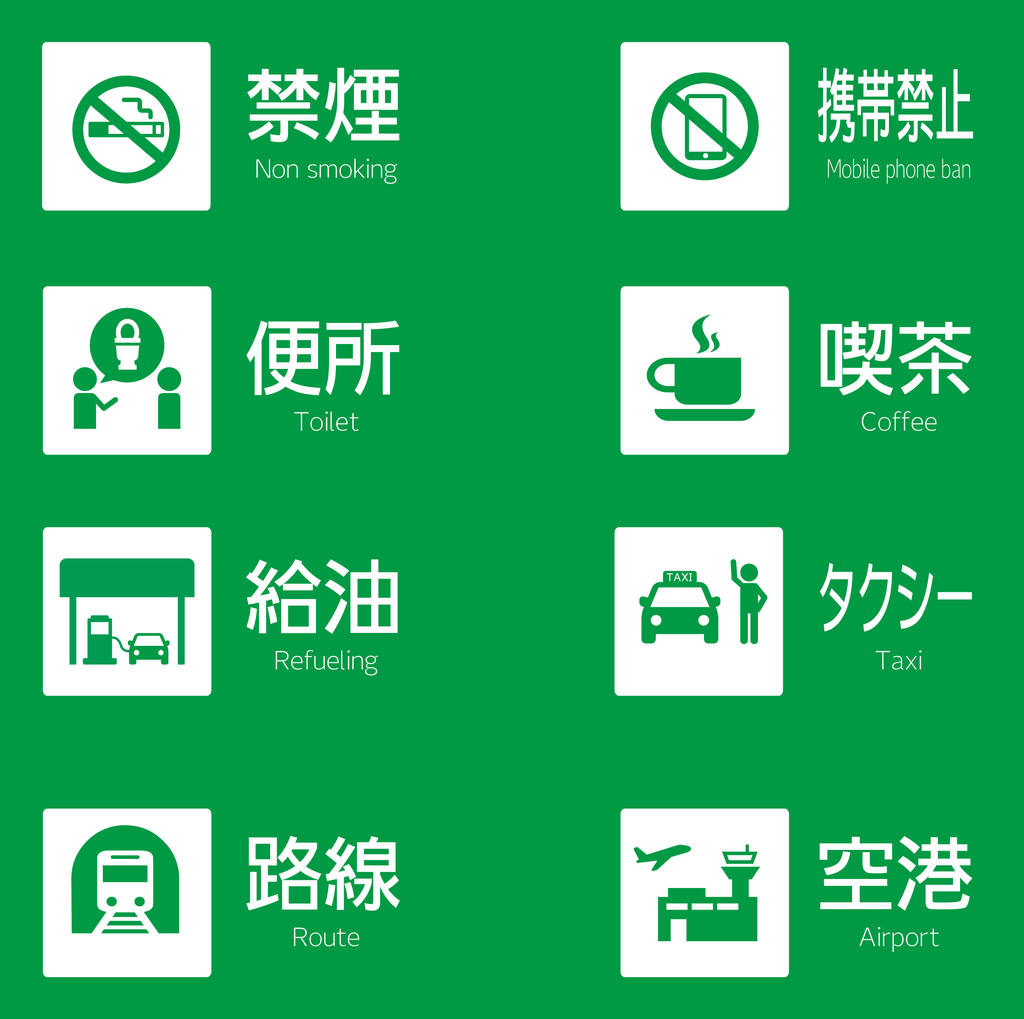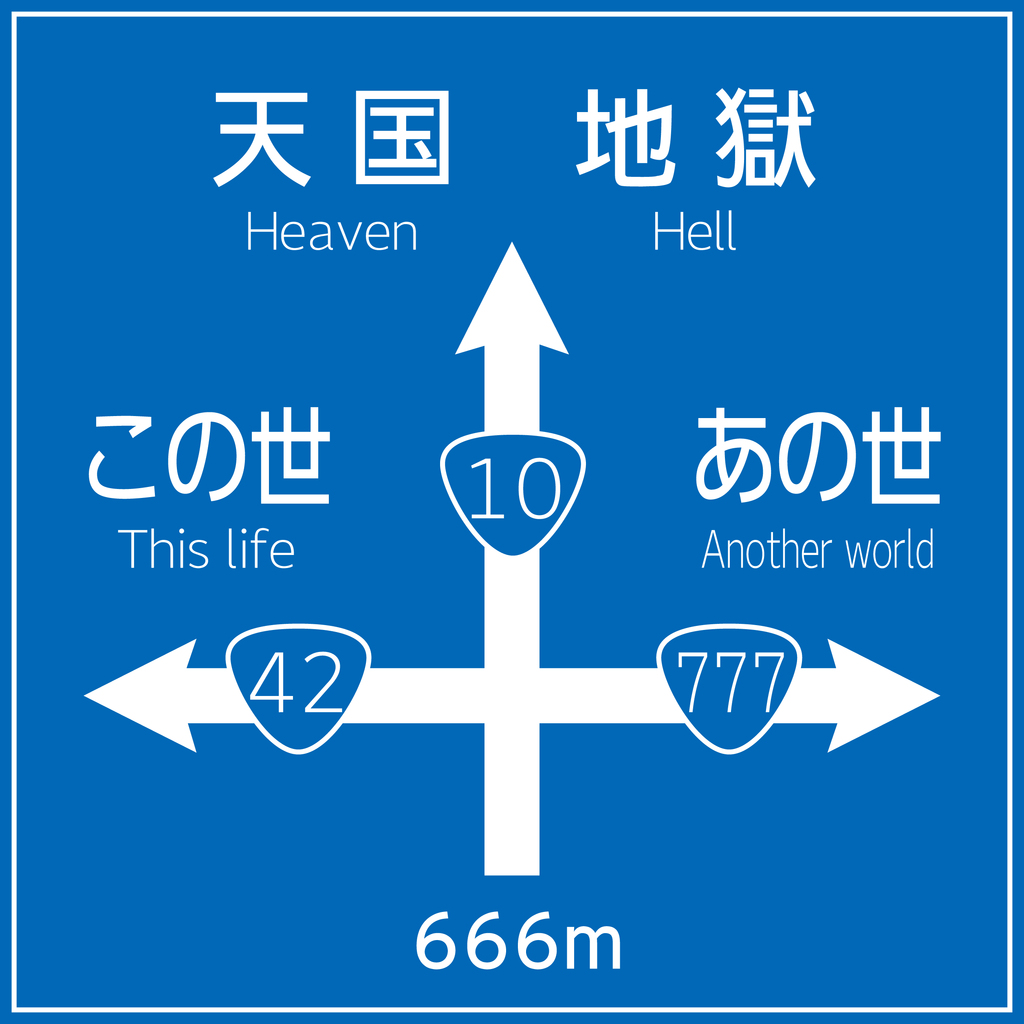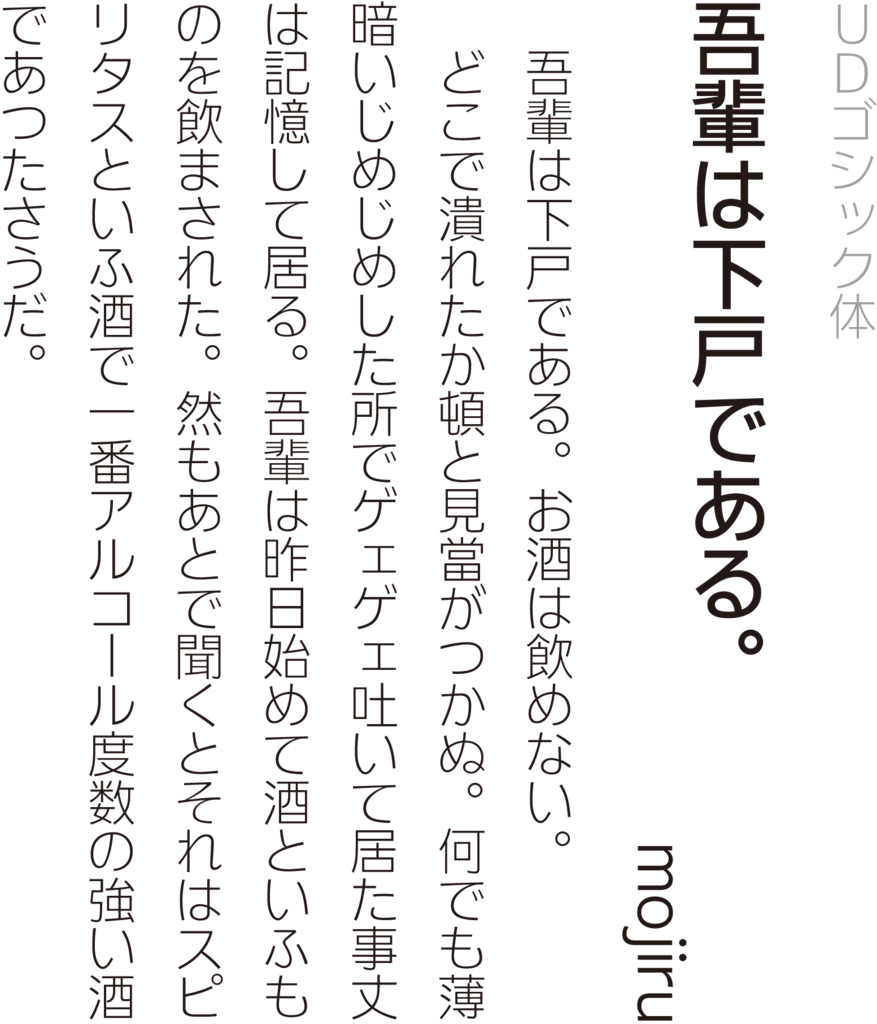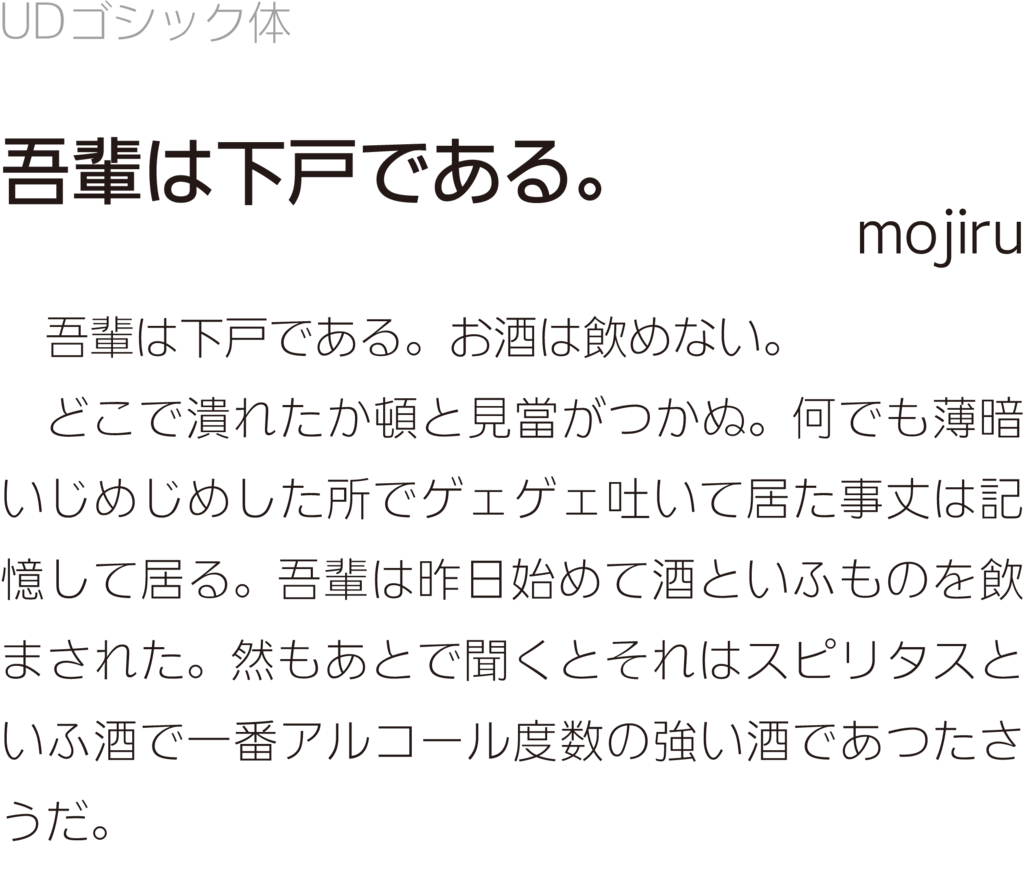
UDゴシック体
ユニバーサルデザインをコンセプトに開発された可読性・視認性・判読性に優れたゴシック体。新聞や取扱い説明書、約款、看板などの印刷物はもとより電子機器における表示やカーナビ、地図、スマートフォン・タブレットなどにおいても正確な情報を読みやすく伝達できる文字ツールになっている。
日本語版UDゴシック体に続き、2020年6月5日に同一デザインによる繁体字中国語版UDゴシック体、簡体字中国語版UDゴシック体がリリースされ、ダイナフォント年間ライセンス「DynaSmart V」に収録された。
UDゴシック体の書体見本
UDゴシック体使用事例「イクリプス録ナビ」
中国語UDフォント「UDゴシック体 繁体字中国語」「UDゴシック体 簡体字中国語」が2020年6月5日に「DynaSmart V」に収録された。
「UDゴシック体 繁体字中国語」「UDゴシック体 簡体字中国語」は、ユニバーサルデザインをコンセプトに日本語フォントとして、先行開発した可読性・視認性・判読性に優れた「UDゴシック体」の中国語版フォント。
それぞれW2、W4、W6で展開。
UDゴシック体 繁体字中国語
繁体字中国語は、簡略化を経ていない筆画が多い漢字の字体体系。ユニバーサルデザインに基づいて開発された繁体字ゴシック体フォント。
UDゴシック体 簡体字中国語
簡体字中国語は、中華人民共和国で制定された従来の漢字を簡略化した字体体系。ユニバーサルデザインに基づいて開発された簡体字ゴシック体フォントとなる。